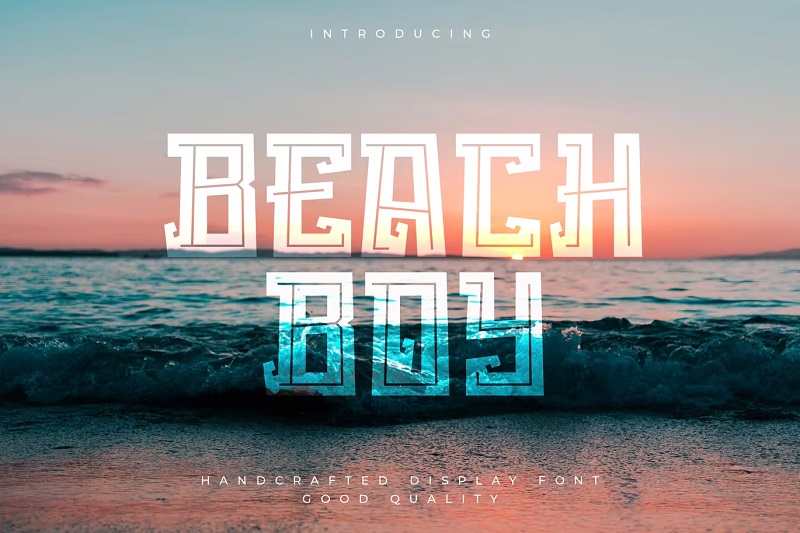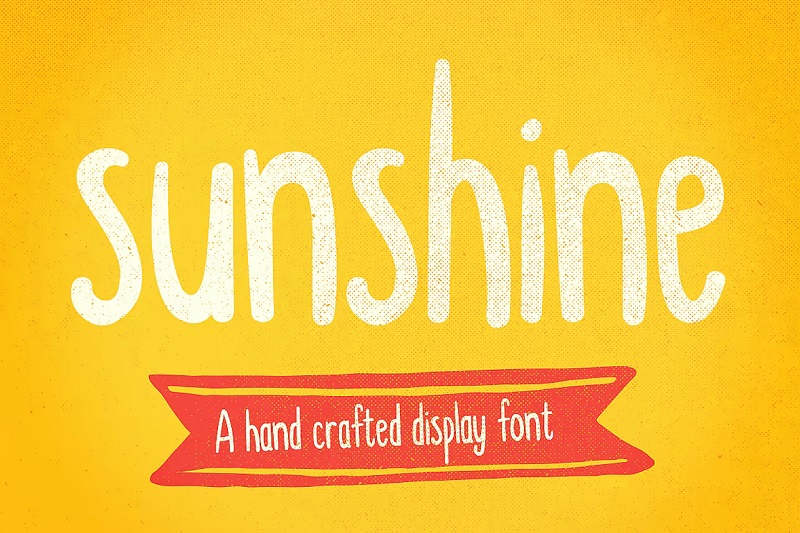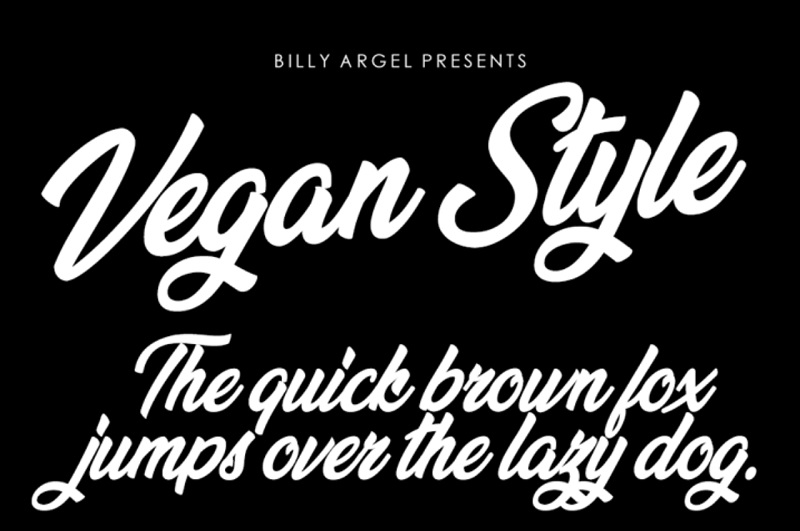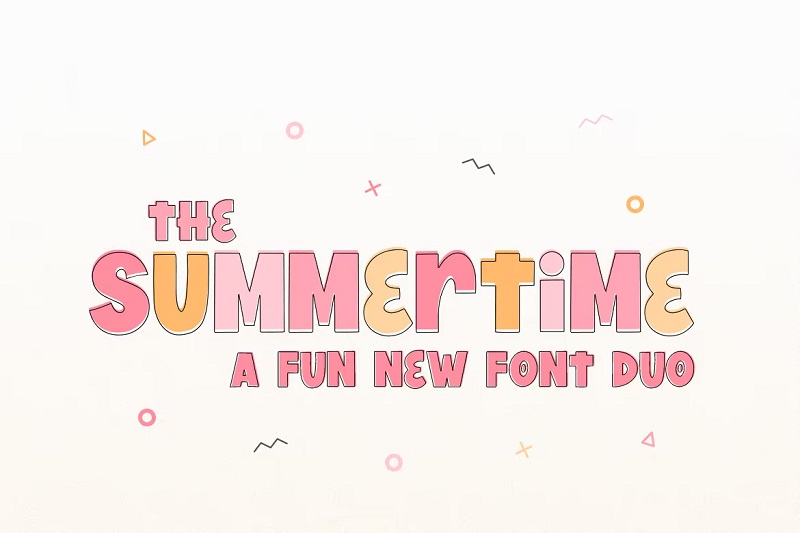
30 beste Sommerschriften, um Ihre Designs aufzuheizen
Veröffentlicht: 2022-03-23Suchen Sie nach sommerlichen Schriftarten für Ihre tropischen Designs? Wir geben dir Deckung.
Nachfolgend haben wir die heißesten Sommerschriften auf dem Markt aufgelistet. Alle unten aufgeführten sonnigen Schriftarten wurden von professionellen Designern erstellt – und sie alle haben die sommerliche Atmosphäre, nach der Sie suchen.
Die Schriftarten auf dieser Liste erinnern an Sand, Meer und Sonne und eignen sich daher hervorragend für Dinge wie Urlaubsbroschüren, Strandhausbeschilderung und Reise-Vlog-/Blog-Banner.
Die 30 besten Sommerschriften
Bereit? Dann lass uns hineinspringen. Hier ist eine Liste der besten kostenlosen und Premium-Sommerschriften, die derzeit erhältlich sind.
1. Summering – Unsere Top -Auswahl
Summering ist eine lustige handgeschriebene Schriftart von Stefaniletter. Es hat eine frische, freundliche Ästhetik mit deutlichen, abgerundeten Buchstaben, die wirklich auffallen. Es ist PUA-codiert und wird mit speziellen alternativen Glyphen und Ligaturen geliefert, die Sie verwenden können, um Ihren Designs visuelles Interesse zu verleihen.
Warum es unsere erste Wahl ist
Summering ist die beliebteste Sommerschrift für Envato-Elemente – und das aus gutem Grund. Es ist voll von der Art von Wärme und Energie, die man mit dem Sommer verbindet. Die Buchstabenformen sind voller Charakter, aber dennoch gut lesbar, was sie zu einer sehr vielseitigen Schrift macht. Es würde in so ziemlich jeder Art von Design gut funktionieren.
2. Sommerflamme
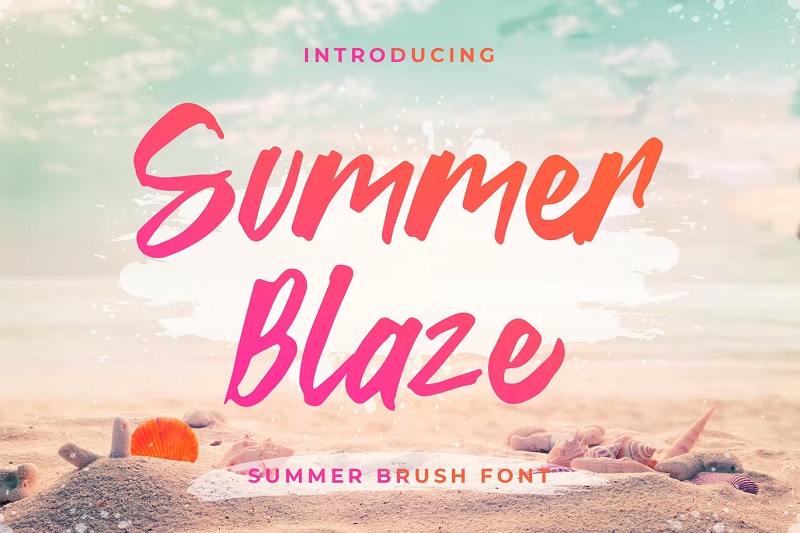
Summer Blaze ist eine superheiße Pinselschrift von Typefactoryco. Es scheint Wärme und Entspannung auszustrahlen. Probieren Sie es aus, um es für ein frisches, auffälliges Aussehen zu Ihrem Strandcafé oder Surfshop-Schild hinzuzufügen.
3. Sommerblues
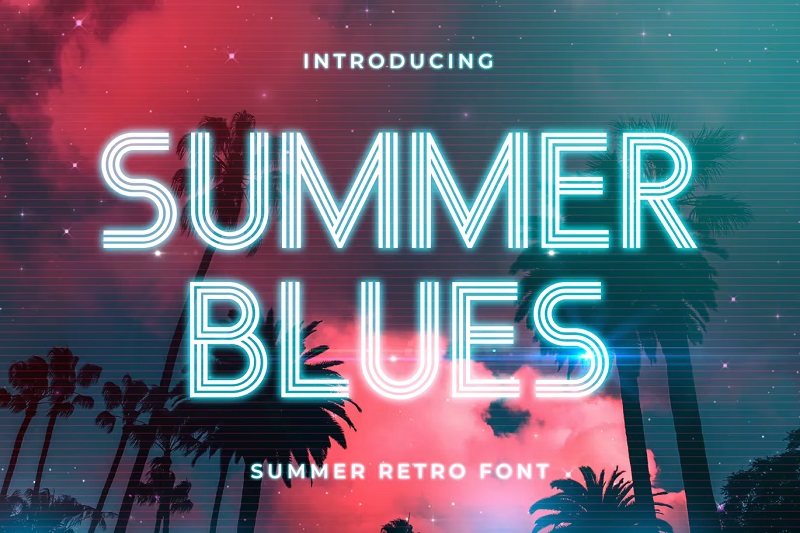
Machen Sie eine Reise in die Vergangenheit und erleben Sie diese glorreichen Sommernächte mit Summer Blues noch einmal. Diese Retro-Neonschrift weist Buchstabenformen auf, die aus drei aufeinanderfolgenden Strichen bestehen, und sieht am besten vor dunkleren Hintergründen aus. Es ist ideal für Nachtclub-Branding, Filmplakate und Zeitschriften.
4. Die Flut
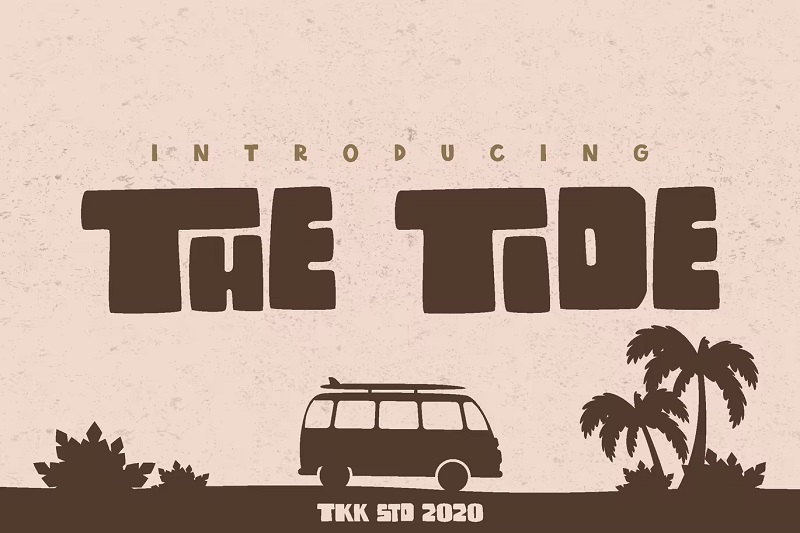
An alle Reise-Vlogger und Van-Lifer – wir haben die perfekte Schriftart für Ihre Marke gefunden.
The Tide ist eine atemberaubende, klobige Schriftart, die an Abenteuer in der Sonne erinnert. Sein sorgloses, rebellisches Design würde in Surfshops, YouTube-Covern, Filmtiteln und Postern und allen anderen Surf- oder Sonnenprojekten großartig aussehen.
5. Alloha
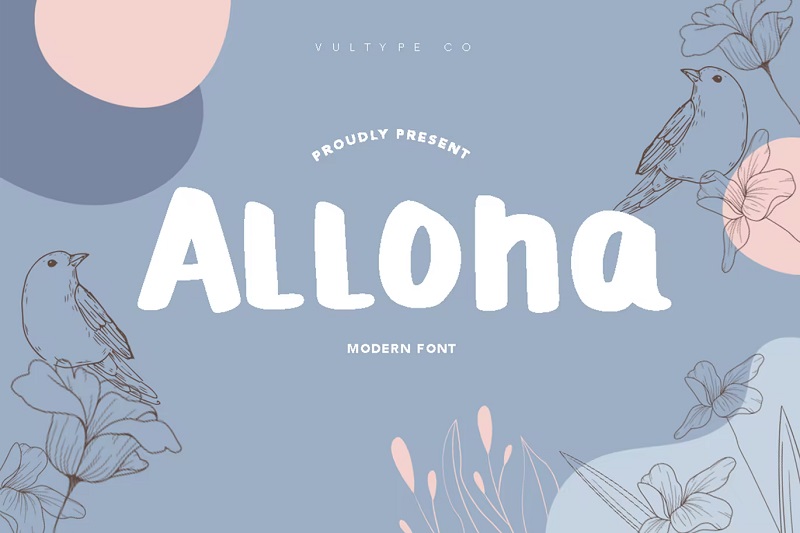
Möchten Sie Ihren Designs eine polynesische Atmosphäre verleihen? Schauen Sie sich Alloha an – eine hawaiianisch inspirierte Sommerschrift von Vultype. Das verspielte, moderne Design und die einzigartigen Buchstabenformen würden bei jedem Projekt zum Thema Sommer großartig aussehen. Es ist im TTF- und OTF-Format erhältlich und kann mit Photoshop, Illustrator, Word, Canva und so ziemlich jeder anderen Designsoftware aufgerufen werden.
6. Sonnenscheintal
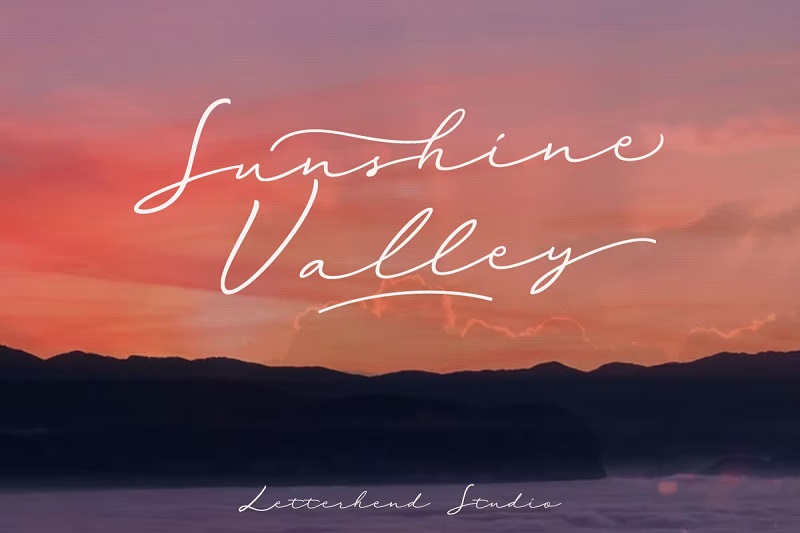
Wenn Sie einen eleganten, femininen Look in Ihren Sommerdesigns suchen, versuchen Sie es mit Sunshine Valley. Diese Monoline-Schrift von Designer Letterhead ist super romantisch und stilvoll. Die kursive Schrift sieht aus, als wäre sie sorgfältig von Hand geschrieben worden, sodass sie auf formellen Einladungen zu einer Strandhochzeit sowie auf Schreibwarenverpackungen und Modeprodukten wirklich gut aussehen würde.
7. Palmsprings
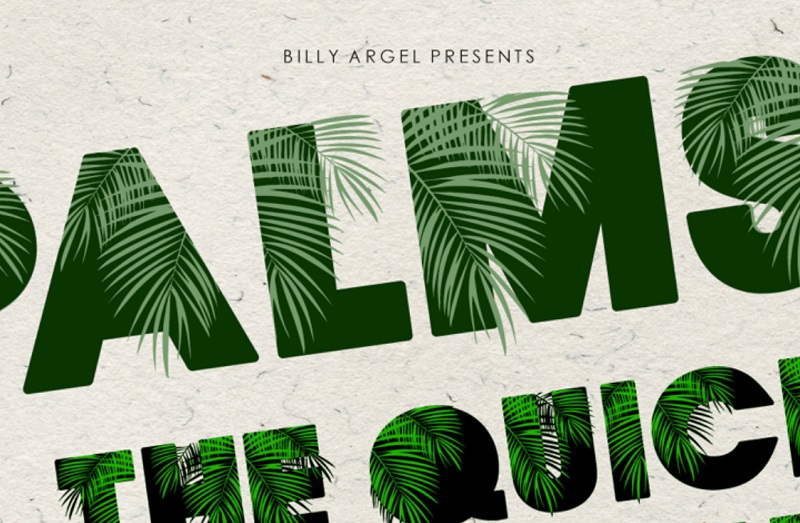
Palmsprings ist eine Sammlung dreischichtiger Schriftarten des Designers Billy Argel. Es verfügt über ein cooles Palmendesign mit Blockbuchstaben in Großbuchstaben, die mit Palmblättern überlagert sind. Glaubst du nicht, dass es sehr gut zu tropischen und Strand-Designs passen würde?
Abschließende Gedanken
Damit ist unsere Zusammenfassung der besten Sommerschriften auf dem Markt abgeschlossen.
Hoffentlich haben Sie in dieser Liste die perfekte Schriftart für Ihr Design gefunden. Wenn nicht, finden Sie in dieser Sammlung fantastischer Schriftarten weitere Ideen, die Sie in Ihren Designs verwenden können.